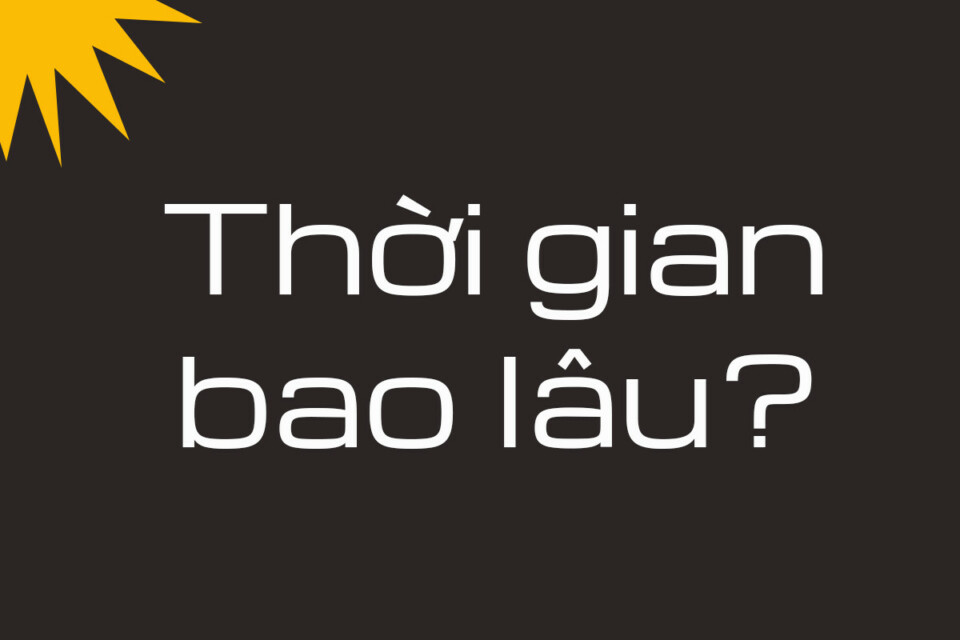
Font việt hóa MJ Michroma – Sự Lựa Chọn Hoàn Hảo Cho Thiết Kế Hiện Đại
Trong thế giới thiết kế đồ họa, việc tìm kiếm một bộ Font Chữ đáp ứng được cả yếu tố thẩm mỹ lẫn tính ứng dụng cao là vô cùng quan trọng. Font việt hóa MJ Michroma nổi lên như một giải pháp lý tưởng dành cho những ai yêu thích phong cách tối giản, hiện đại và mang hơi hướng tương lai. Được tinh chỉnh kỹ lưỡng để phù hợp với bảng mã tiếng Việt, bộ font này giúp các nhà thiết kế loại bỏ hoàn toàn nỗi lo lỗi font khi gõ dấu.
Đặc điểm nổi bật của Font việt hóa MJ Michroma
Bộ Font việt hóa MJ Michroma gây ấn tượng mạnh mẽ nhờ cấu trúc chữ hình học sắc nét và các đường nét tròn trịa đầy tinh tế. Đây là kiểu chữ không chân (sans-serif) được tối ưu hóa cho hiển thị kỹ thuật số, đảm bảo độ sắc nét ngay cả trên các thiết bị có độ phân giải thấp.
Tính ứng dụng linh hoạt trong học tập và giảng dạy
Đối với học sinh và giáo viên, Font việt hóa MJ Michroma cực kỳ hữu ích trong việc trình bày slide bài giảng hoặc làm báo cáo dự án. Sự rõ ràng của từng mặt chữ giúp người xem dễ dàng tiếp nhận thông tin, tạo nên sự chuyên nghiệp và trực quan cho nội dung giáo dục. Bạn có thể sử dụng nó cho cả tiêu đề chính lẫn các đoạn văn bản ngắn để tạo điểm nhấn.
Để đạt hiệu quả tốt nhất, bạn nên kết hợp font chữ này với các tông màu trung tính hoặc phong cách thiết kế phẳng. Sự đơn giản của nó sẽ làm nổi bật ý tưởng sáng tạo mà không gây rối mắt cho người xem. Nếu bạn đang tìm kiếm một công cụ hỗ trợ thiết kế chuyên nghiệp, đừng bỏ qua Font Miễn Phí, Font Việt Hóa, Font việt hóa MJ Michroma để nâng tầm sản phẩm của mình ngay hôm nay. Hy vọng bộ font này sẽ trở thành người bạn đồng hành tin cậy trong hành trình học tập và sáng tạo của bạn.